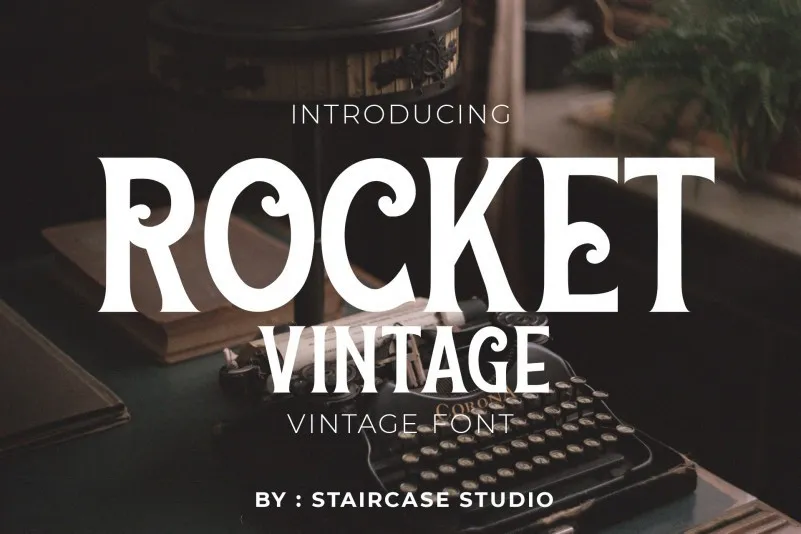
Aqui está uma descrição em português do Brasil para a página de download da font ‘Rocket Vintage Font’, com 2 parágrafos curtos e no estilo solicitado: Com seu look retro e vintage, a Rocket Vintage Font é perfeita para os designers que buscam trazer um toque nostálgico às suas criações. Esta tipografia moderna e elegante transformará qualquer design em algo incrivelmente inspirador. Seja você um designer de logotipos ou uma marca digital, essa fonte tem o potencial de dar vida a seu projeto. Além disso, sua versão numérica é igualmente útil, tornando-a perfeita para as aplicações como logomarcas e arte digital, bem como publicidade impressa em panfletos, revistas ou sinais. Para quem busca um design mais estilizado, a Rocket Vintage Font oferece uma variedade de letras e números que se adequam ao seu projeto. Ela também é ideal para criações digitais em t-shirts e roupas, aplicações gráficas em outdoors, e qualquer necessidade de design. Numa palavra: incrível.
Designer: Tommy Soft